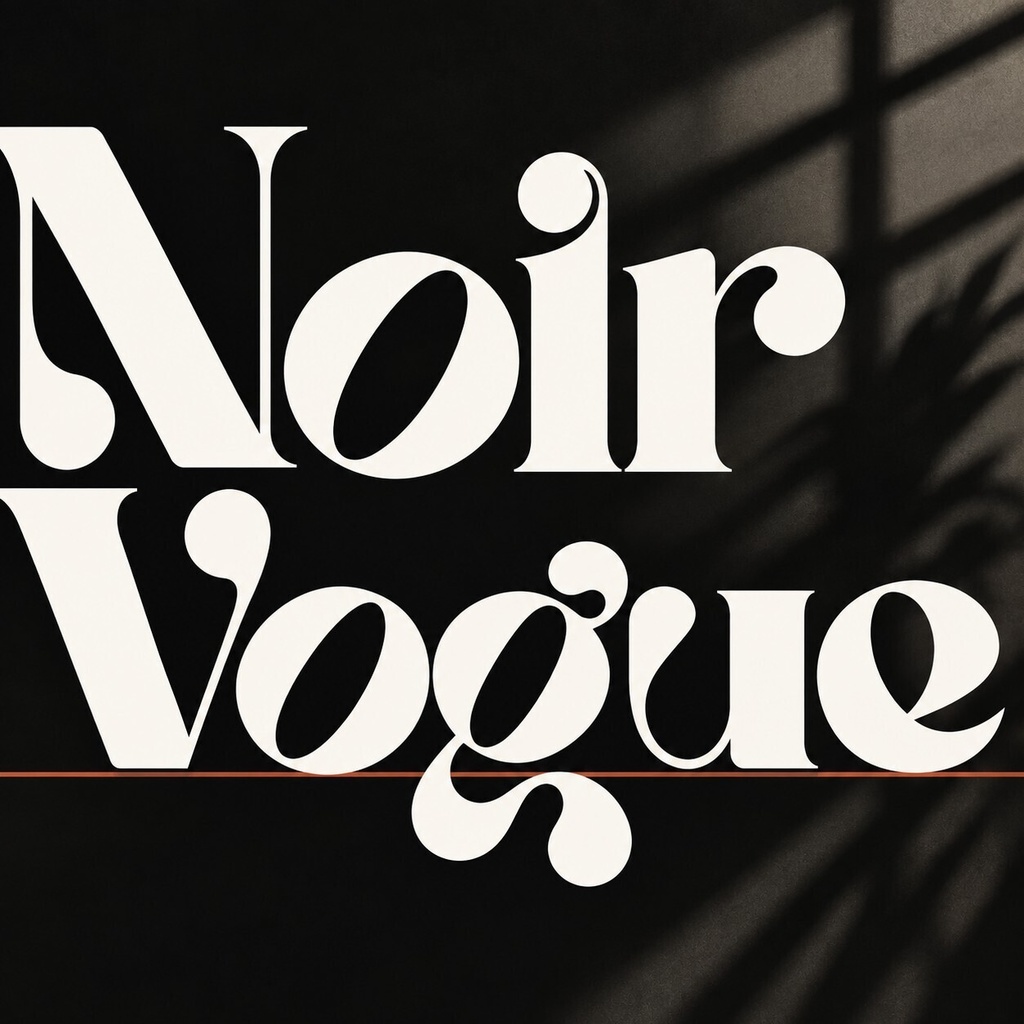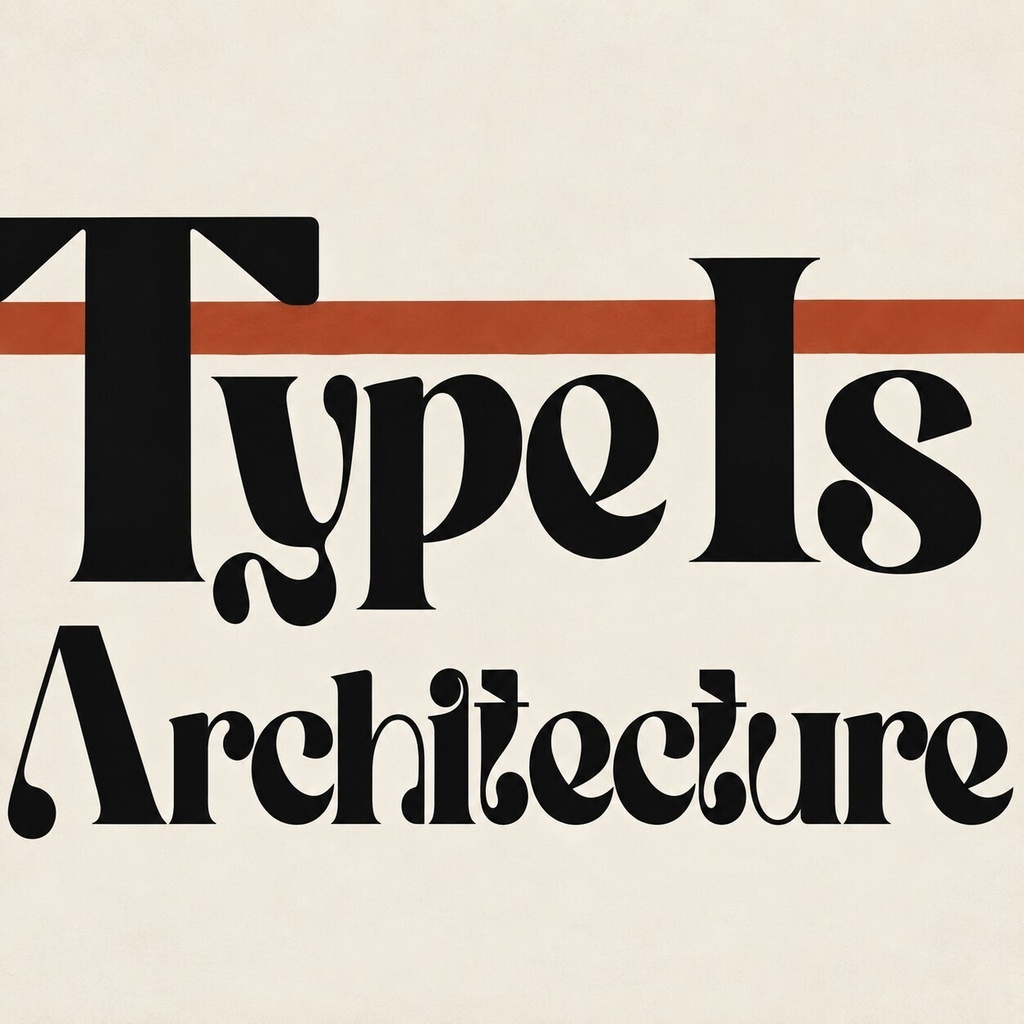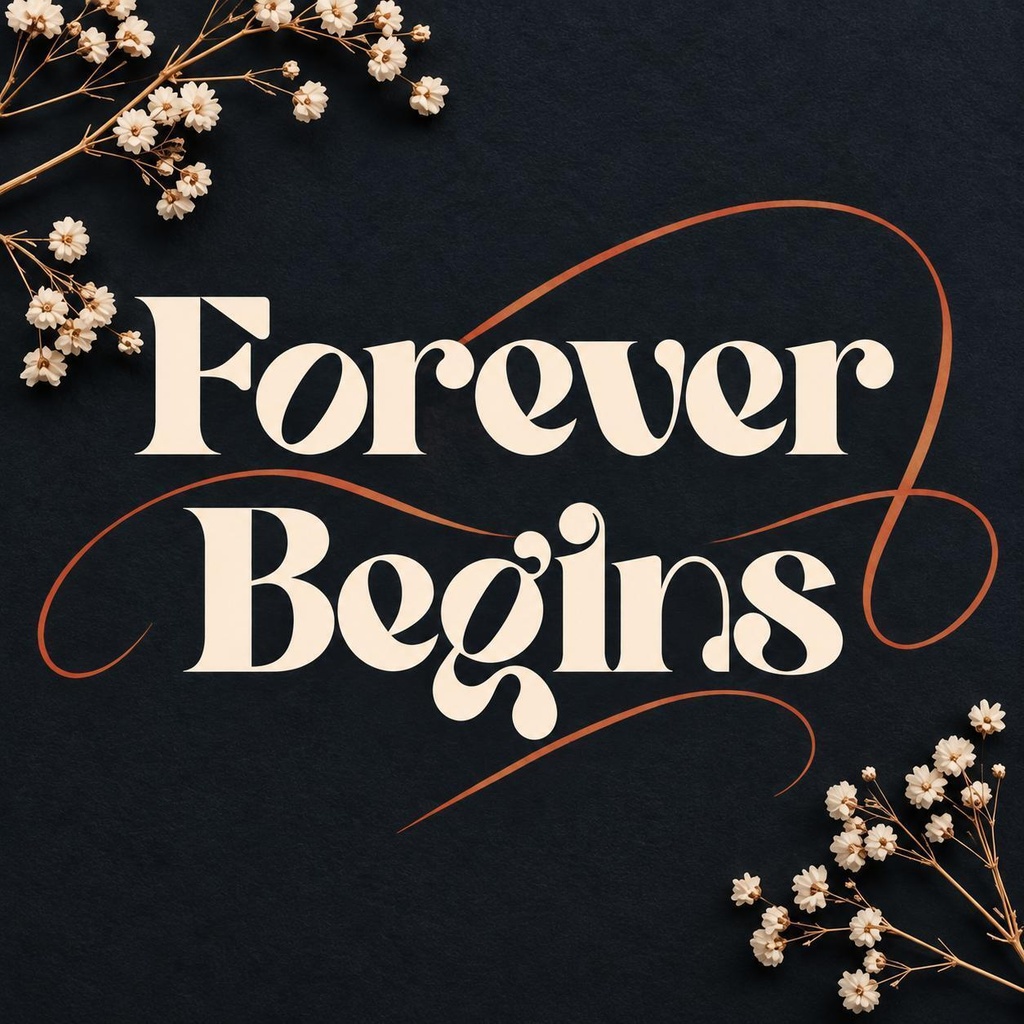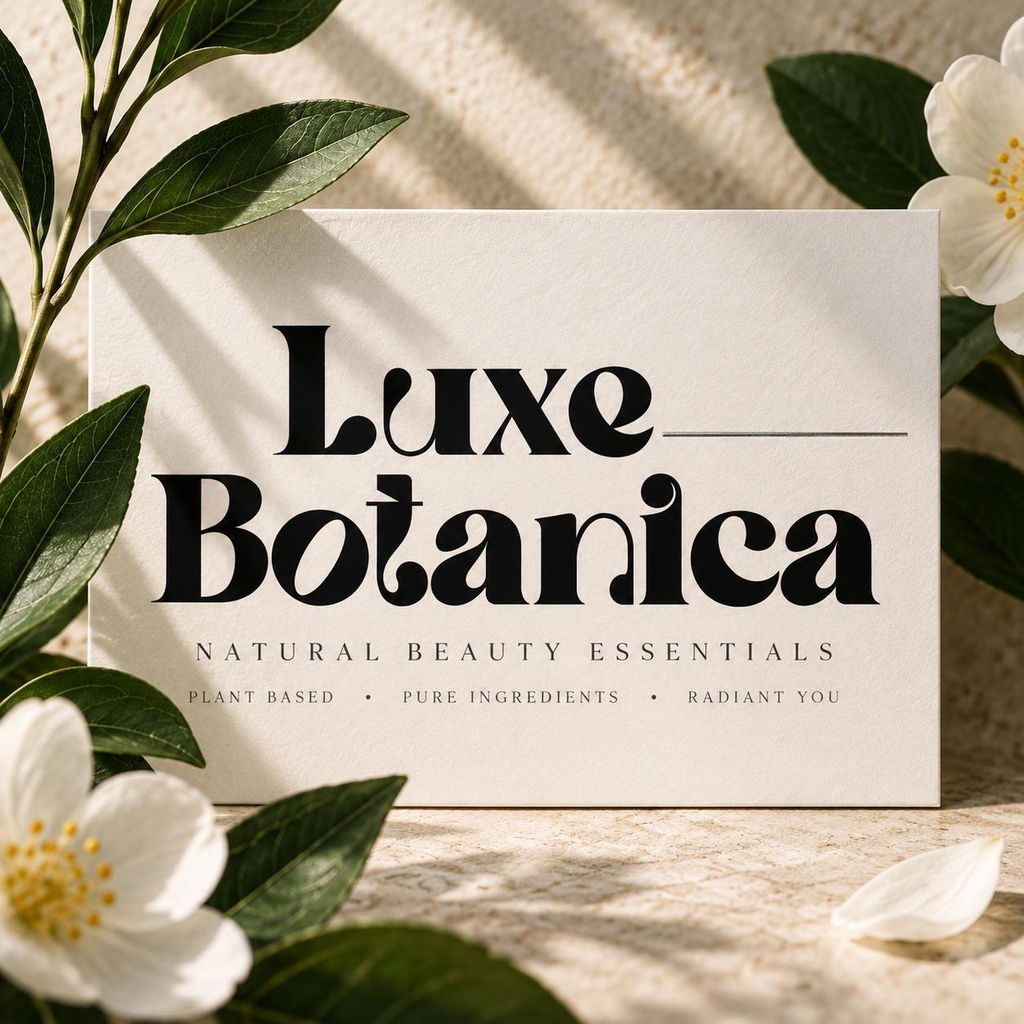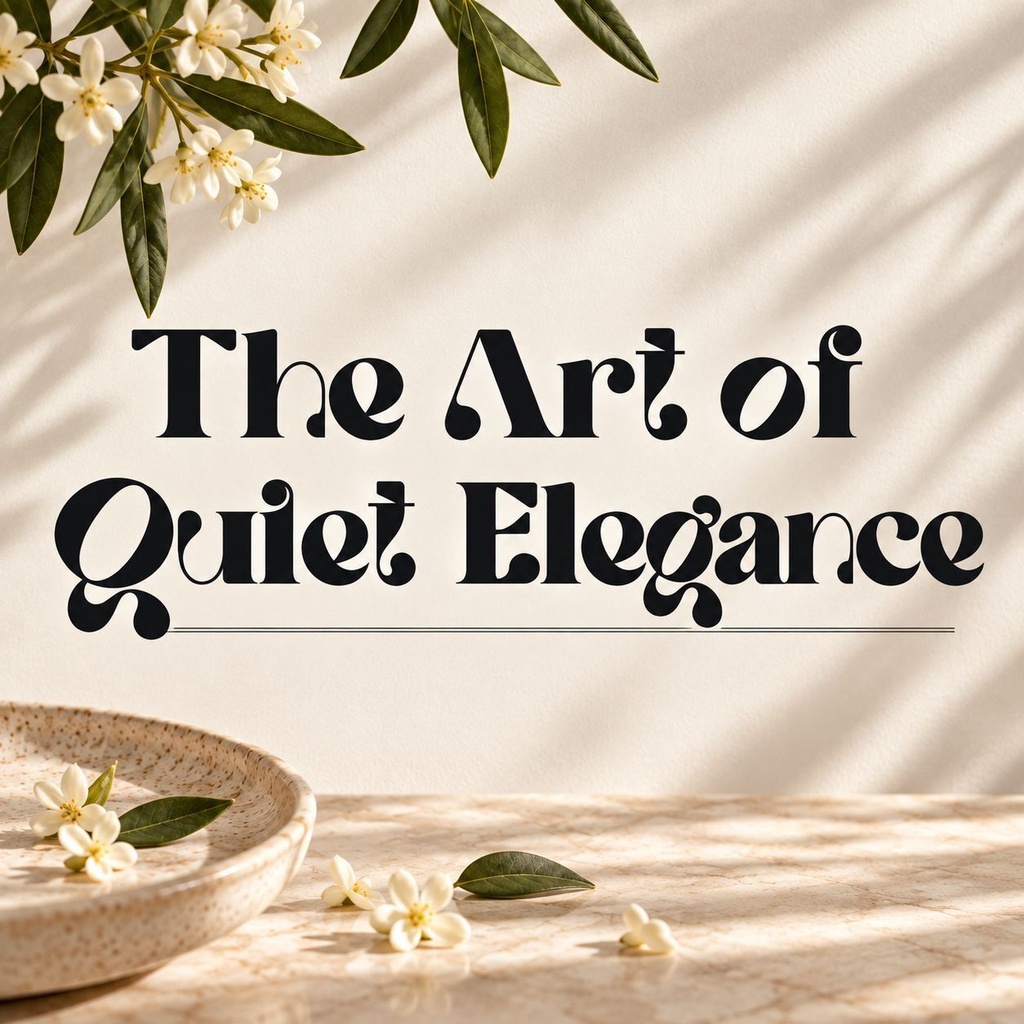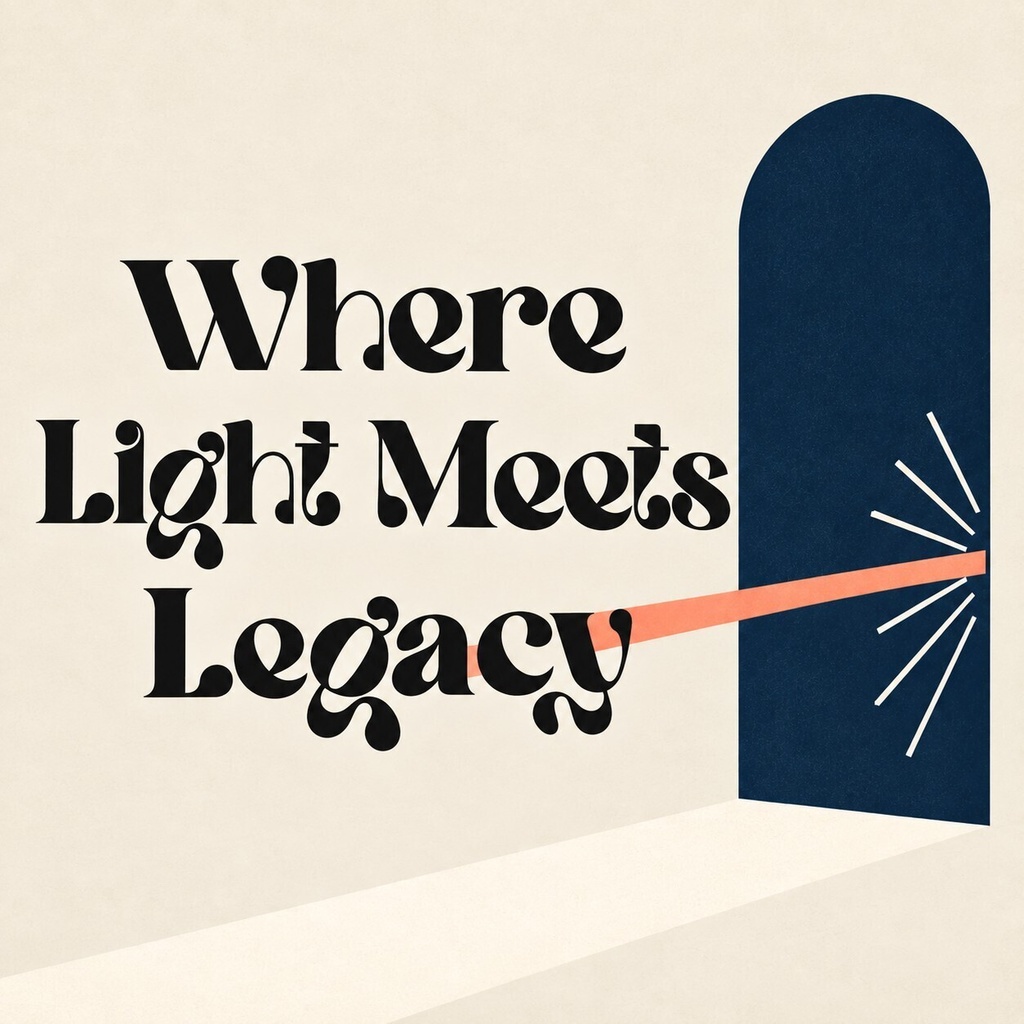
Quill Crest(クイル・クレスト)【セリフフォント】
高コントラストの太細ストロークとシャープなセリフディテールが特徴のモダンセリフフォントです。洗練されたエレガンスと力強いビジュアルインパクトを同時に実現し、ロゴデザイン・ファッションブランディング・エディトリアル見出し・ウエディング招待状・コスメパッケージ・ブランドラベル・高級マーケティング素材など、印象に残るデザイン制作に最適です。 Quill Crest は、近代的なプロポーションと鋭いセリフ先端を融合したディスプレイ書体です。大タイトルやステートメントタイポグラフィで、オリジナリティと品格を発揮します。 ## 収録内容 - フォントファイル一式(OTF, TTF, WOFF, WOFF2) - 大文字・小文字、数字、句読点 - 多言語対応(ä ö ü Ä Ö Ü ß ¿ ¡) ## 対応文字 - 英語アルファベット(A-Z, a-z) - 数字(0-9) - 記号・句読点 - 多言語アクセント文字(ラテン拡張) ## 用途 - ロゴデザイン・ブランディング - ファッションブランド・ビューティー - エディトリアル見出し・雑誌表紙 - ウェディング招待状・ステーショナリー - コスメパッケージ・ボトルラベル - 高級ブランドラベル・タグ - マーケティング素材・ポスター - ゲームタイトル・ビジュアルロゴ ## 形式 - OTF(OpenType Font) - TTF(TrueType Font) - WOFF(Web Open Font Format) - WOFF2(Web Open Font Format 2) ## 対応環境 - macOS / Windows / Linux - Adobe Photoshop / Illustrator / InDesign - Figma / Sketch / Canva - 主要なグラフィックソフトウェア ## 利用許諾 本フォントは商用利用可能(Commercial Use)です。ロイヤリティフリーで、ビジネス・クライアント向け・有料・ブランド化・広告・グッズ制作に使用できます。個人利用(Personal Use)版は、購入者自身の非商用プロジェクト・学習・練習・プライベート制作に使用できます。詳細は付属のライセンスファイルをご確認ください。